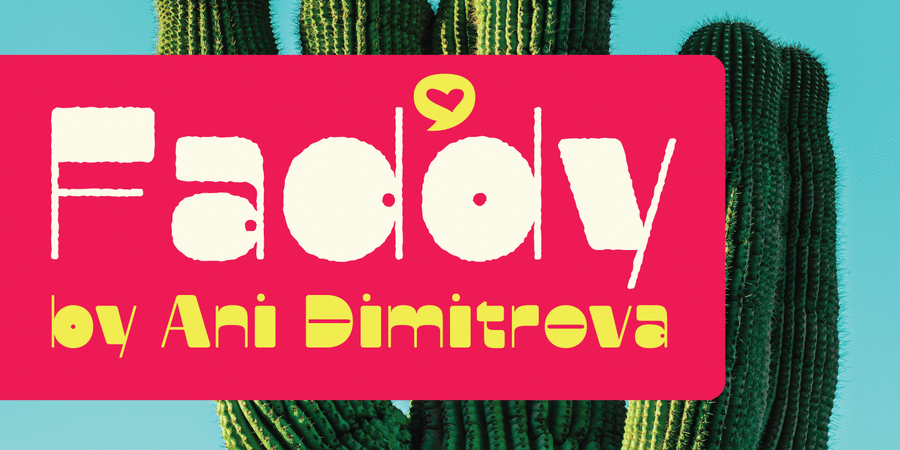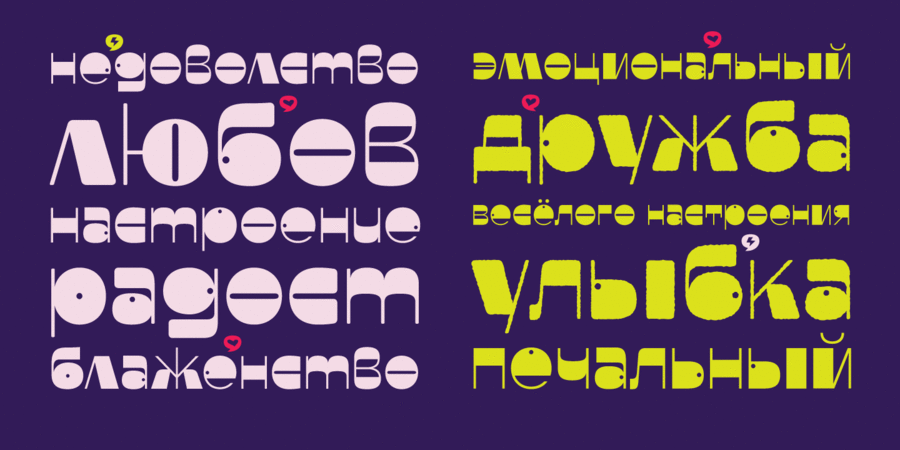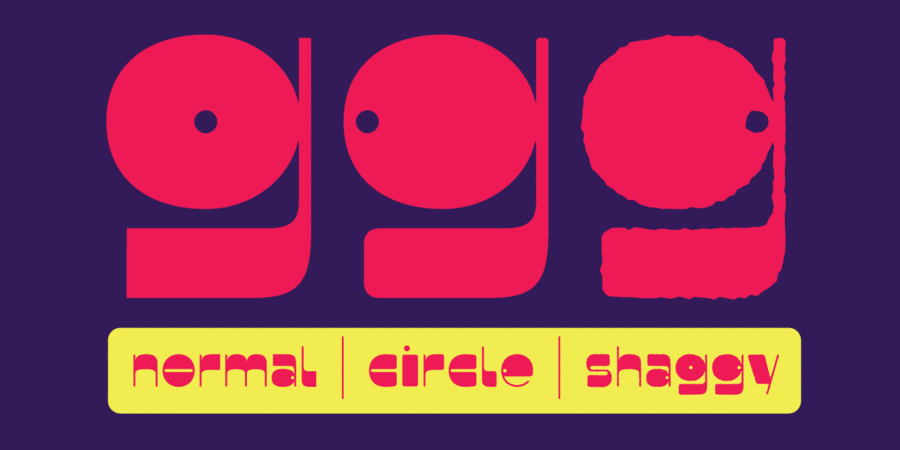
Faddy (3 шрифта)
Він завжди свіжий, усміхнений, трохи божевільний, іноді сердитий, часто розпливчастий, а також може бути дуже кумедним. З Faddy ви можете писати багатьма мовами. Шрифт містить 3 різні накреслення – звичайне, заокруглене та кошлате. Кожне накреслення містить понад 500 гліфів, а також необхідні функції OpenType: індекси, табличні цифри, стрілки, символи валют і дроби. У Faddy також є багато кумедних стилістичних наборів і варіантів літер, які можуть надати йому інший настрій та вигляд. Шрифт розробила Ані Дімітрова в 2020 році.
3 накреслення
Особливості сімейства шрифтів FaddyХіт десятиліття:
Асоціації з сімейством шрифтів FaddyОсобистість і характер гарнітури:
літній, неформальний, емоційний, енергійний, небувалий, екзотичний, іронічний, нонконформістський, манірний, мінливий, оманливий, епатажний, оригінальний, виразний, святковий, радісний, позитивний, дитячий, наївний, милий, артистичний, музичний, ритмічний, грайливий, веселий, цікавий, задерикуватий, характерний, привітний, прикольний, доброзичливий, добродушний, вигадливий, смішний, самобутній, неординарний, мажорний, інфантильний, легковажний, хитрий, динамічний, дивний, усміхнений, щасливий, творчий, симпатичний, тусовочний, потішний, помітний, яскравий, театральний, демонстративний, активний, круглий, гучний, мультяшний, пустотливий, свіжий, важкий, дотепний, домашній, щедрий, живий, дзвінкий, різкий, чіткий, товстий, М'який, стиглий, соковитий, смачний, апетитний, затишний, пузатий, рукотворний, приємний, ламповий, вінтажний, добрий, теплий, спекотний, пластмасовий, спекотливий, запальний, пухнастий, ручний